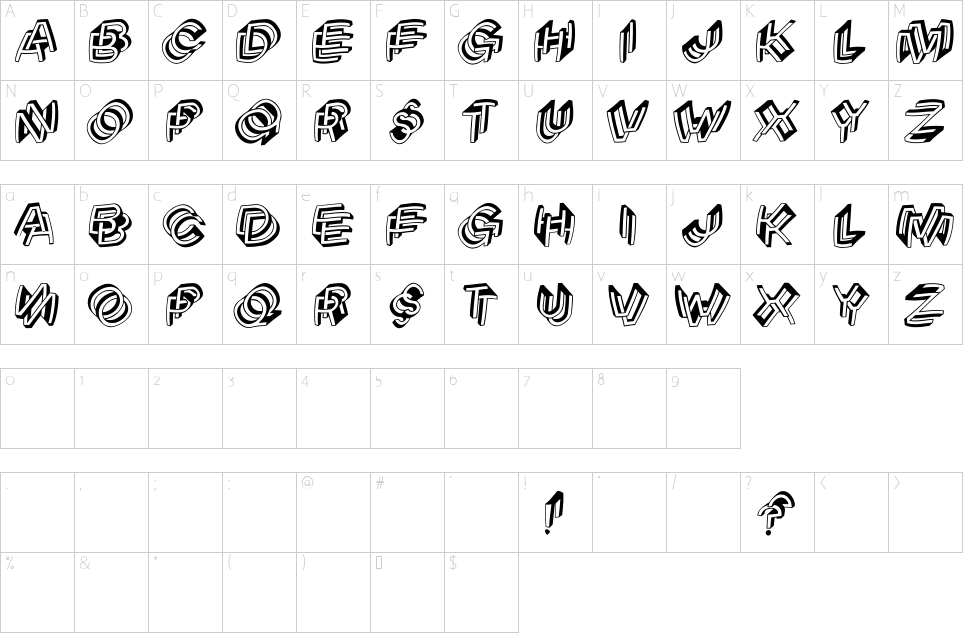
A Architypogra é uma fonte meticulosamente projetada pelo arquiteto Manfred Klein, que proporciona um equilíbrio perfeito entre clareza e elegância. Esta fonte é uma escolha ideal para quem busca uma solução de fonte que se destaca em qualquer aplicação, seja para trabalhos de texto ou criações visuais. Ela oferece uma experiência de escrita suave e harmoniosa, que se adapta perfeitamente a múltiplas aplicações, tornando-a uma fonte versátil e versátil. Se você está procurando por uma fonte que ofereça tanto profissionalismo quanto facilidade de uso, a Architypogra pode ser o ponto de partida perfeito. Sua simplicidade e beleza tornam-a uma escolha ótima para profissionais de design, desde arquitetos e designers de jogos até web designers e gráficos.